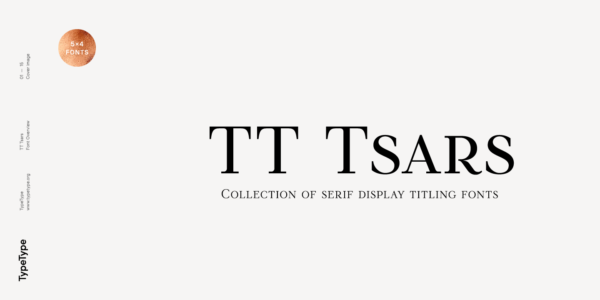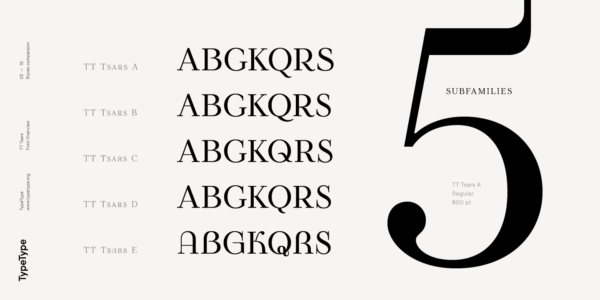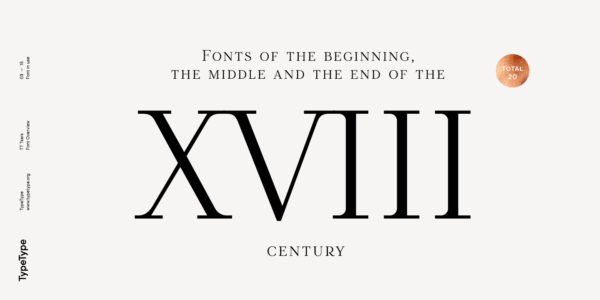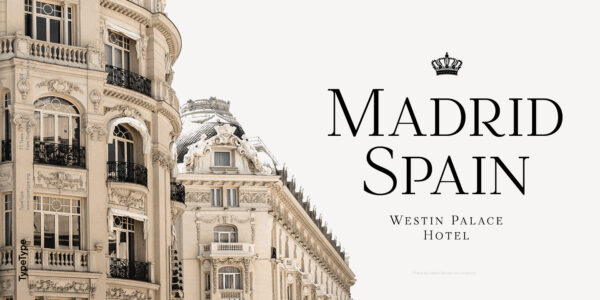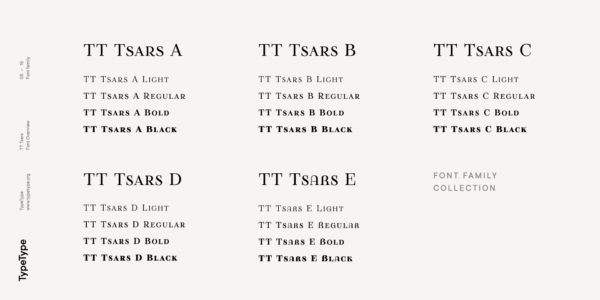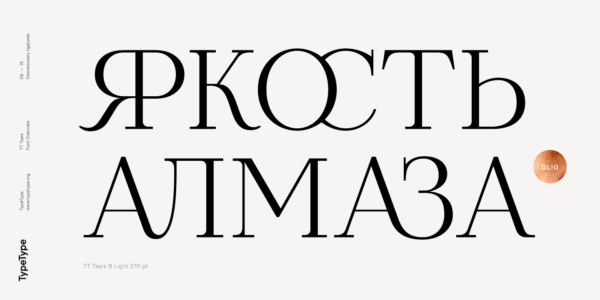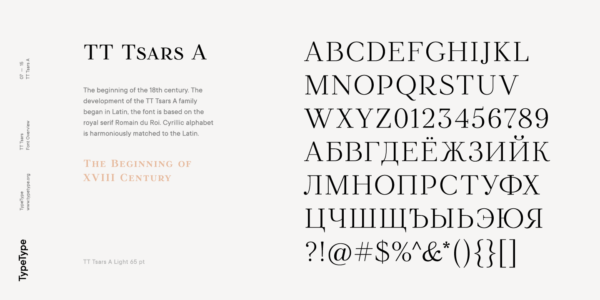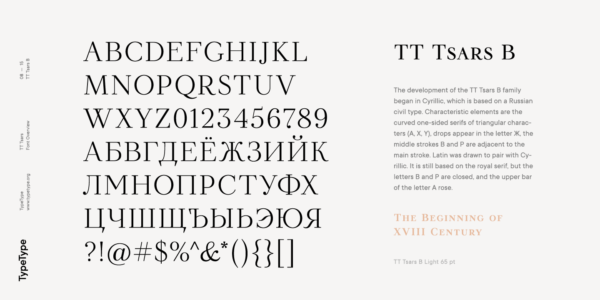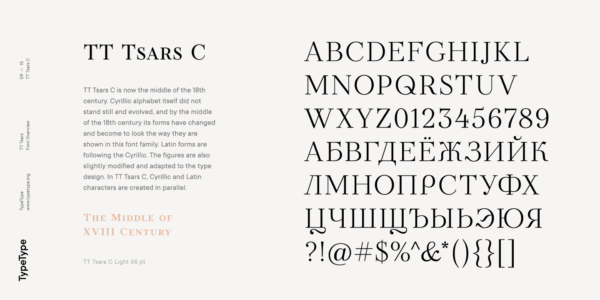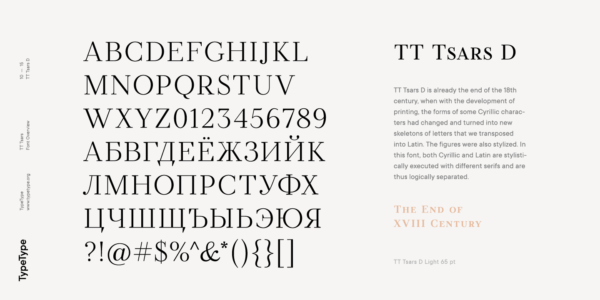
TT Tsars
TT Tsars — ТТ Царс
Произносится «ТТ Царс». «Tsars» — производное слово от английского tsar (царь). Буквы «TT» являются аббревиатурой названия компании.
TT Tsars — ​​коллекция акцидентных антикв. Все они стилизованы под аутентичные шрифты XVIII века, которые использовались для оформления книжных титулов.
TT Tsars
Коллекция акцидентных титульных антиквенных шрифтов
TT Tsars
В основу проекта легли титульные шрифты, то есть те шрифты, которыми оформлялись, в частности, книжные титулы. Идея для проекта TT Tsars родилась после небольшого исследования об историческом развитии кириллического шрифта, и в том числе базируется на книге Шицгала «Русский гражданский шрифт».
TT Tsars
Мы разработали базовый универсальный скелет для форм всех знаков у всех подсемейств гарнитуры
TT Tsars
В TT Tsars можно найти большое количество лигатур
TT Tsars
TT Tsars в дизайне
О гарнитуре TT Tsars
Шрифтовая гарнитура TT Tsars является коллекция акцидентных титульных антиквенных (serif) шрифтов, стилизованных под начало, середину и конец XVIII века. В основу проекта легли титульные шрифты, то есть те шрифты, которыми оформлялись, в частности, книжные титулы. Идея для проекта TT Tsars родилась после небольшого исследования об историческом развитии кириллического шрифта, и в том числе базируется на книге Шицгала «Русский гражданский шрифт».
В самом начале проекта мы разработали базовый универсальный скелет для форм всех знаков у всех подсемейств гарнитуры, и в дальнейшем уже нанизывали на него стилистику, визуальные особенности, артефакты и прочие нюансы, свойственные выбранным эпохам. Да, возможно с точки зрения исторической точности такой подход не всегда оправдан, но мы достигли поставленной цели и в итоге получили отлично сочетаемые между собой антиквенные шрифты, которые можно использовать для стилизации под определённый временной период.
Шрифтовая гарнитура TT Tsars состоит из 20 шрифтов: 5 отдельных подсемейств, каждое из которых состоит из 4 начертаний. В состав каждого шрифта входит 580 глифов, кроме гарнитуры E, в ней каждый шрифт состоит из 464 знаков. Вместо строчных знаков в шрифтах используется капитель, что тоже намекает на то, что шрифт скорее акцидентный, чем текстовый. В TT Tsars можно найти большое количество лигатур (для латиницы и для кириллицы), стрелки, ручки и много полезных OpenType фич, таких как: frac, ordn, sinf, sups, numr, dnom, case, onum, tnum, pnum, lnum, salt (ss01), dlig.
Временные характеристики между подсемействами распределяются следующим образом:
• TT Tsars A — начало 18 века (латиница и кириллица)
• TT Tsars B — начало 18 века (латиница и кириллица)
• TT Tsars C — середина 18 века (латиница и кириллица)
• TT Tsars D — конец 18 века (латиница и кириллица)
• TT Tsars E — условно начало 18 века (только латиница, киберпанк)
Гарнитуры TT Tsars А и TT Tsars В (обе начало 18 века) отличаются отправной точкой. Для TT Tsars А — это латиница, для TT Tsars В — кириллица. Развитие гарнитуры TT Tsars А начиналось с латиницы, шрифт построен на базе королевской антиквы Romain du Roi. Кириллица максимально гармонично подобрана к латинице.
Развитие гарнитуры TT Tsars В начиналось с кириллицы, в основе которой лежит гражданский шрифт. Характерными элементами являются изогнутые односторонние засечки треугольных знаков (А, Х, У), появляются капли у буквы Ж, средние штрихи В и Р примыкают к основному штриху. Латиница рисовалась в пару к кириллице. Она осталась основанной на королевской антикве, но несколько видоизменилась: закрылась буква В и Р, у буквы А поднялась верхняя перекладина. Это было сделано для визуального объединения кириллицы и латиницы и одновременно разведения между собой TT Tsars А и TT Tsars В.
TT Tsars C — это середина 18 века. Сама по себе кириллица не стояла на месте и эволюционировала и к середине 18 века ее формы изменяются и становятся такими, какими они показаны в данном штифтовом семействе. Латинские формы формы чуть подтягиваются за кириллицей. Цифры также немного изменены и адаптированы под рисунок шрифта. В TT Tsars C кириллица и латиница создаются параллельно. Отличительная черта у кириллицы в TT Tsars C — остаточное влияние плоского пера. Это заметно на таких знаках как З, Ж, К. Очень характерны для эпохи формы букв Р, Ц, Щ, Э. В латинице появляется характерная нога у буквы R. Для обоих языков характерна С с верхней засечкой и появление крупных, даже несколько жирнящих засечек на горизонталях (Т, Е, Г, L).